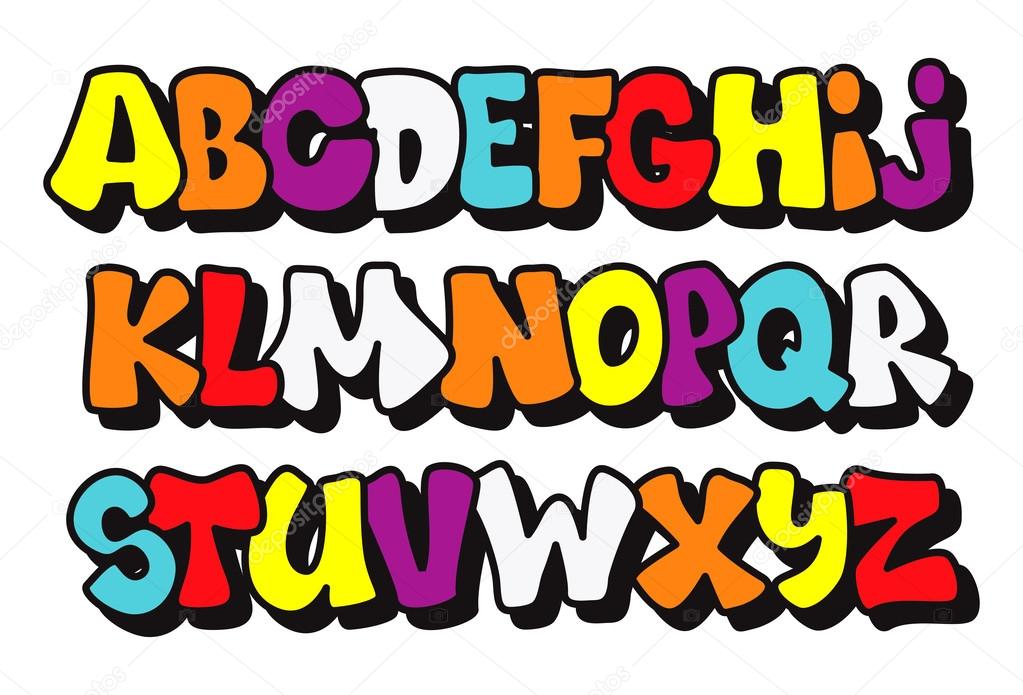
35+ русских толстых и жирных шрифтов, обзор сервиса rus-shrift.ru
Подборки интересных жирных и лучших bold шрифтов были бы неполными без соответствующих русских вариантов. Изначально я думал добавить их к данным статьям, но позже решил написать отдельную заметку, поскольку нашел интересный сервис по кириллическим шрифтам — rus-shrift.ru. Так что сегодня кроме материалов для скачивания будет также небольшой обзор этого проекта. Кстати, вы также можете глянуть сайты онлайн архивы русских шрифтов.Итак, начнем. Для скачивания кликайте по картинкам и переходите на источники. В некоторых случаях придется немного подождать формирования ссылки на загрузку.
v_Holy Mackerel!
WiGuru 2
American Captain Cyrillic
Banana Brick
AA BebasNeue
Equestria Cyrillic
Red October Fat
Sprite Graffiti Shadow
Этот жирных шрифт, конечно, больше похож на граффити однако его все равно можно использовать для броских заголовков.
Fantazyor
High Sans Serif 7
Cathodelic Cyr
RUSXXII Dont Mess With Vikings
Deftone
BeeskneesC
20 db Regular
aAvanteTck Heavy Italic
aBentTitul
InavelTetkaCyr Semi-expanded DemiBold
Micra Bold
New_Zelek Normal
Aksent Normal
FrankC Regular
BIP
aCampusGrav
a_JasperTitulRndNord Regular
Motter Tektura Cyrilic Normal
a_RewinderTitulRgh Bold
ProunX Bold
a_StamperBrk Regular
aBraggaTitulDcFr
a_LatinoTitulBr Regular
aBremen BoldItalic
a_SimplerDnm Regular
Bebit Normal
Жирные русские шрифты на rus-shrift.ru
Отличительной особенностью проекта rus-shrift.ru является то, что в нем, во-первых, содержатся только русские шрифты, а во-вторых, имеется специальный раздел для жирных фонтов.
Материалов в разделе не так много — всего 50 штук, однако мне больше нравится функциональность сервиса. На странице с выбранным шрифтом задаете для него разные настройки: тень, цвет, эффекты и т.п. При этом rus-shrift.ru генерирует готовый код CSS стилей для вставки на свой сайт. Для понимания кода можете глянуть статью блога про реализацию жирных текстов на HTML и CSS.